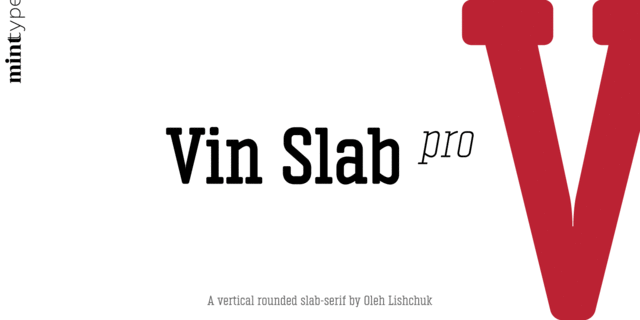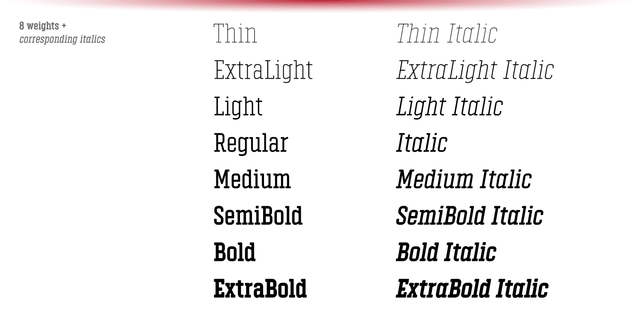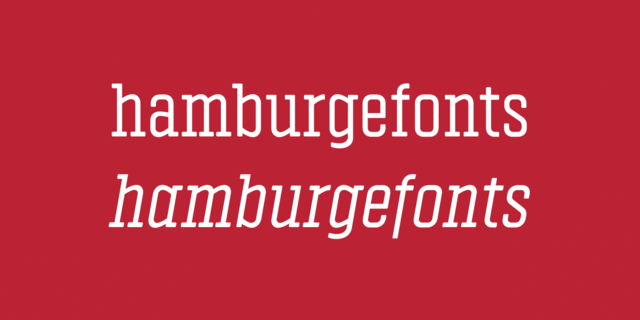
Vin Slab Pro представляет собой сгущенную жесткую брусковую гарнитуру с увеличенным x-height и закругленными углами. Vin – супергарнитура из трех маскулинных шрифтовых семейств с ярко выраженными вертикальными штрихами и закругленными углами. Для большей выразительности все три шрифта имеют увеличенный x-height. Шрифт разработал Олег Лищук в студии Mint Type в 2018 году.